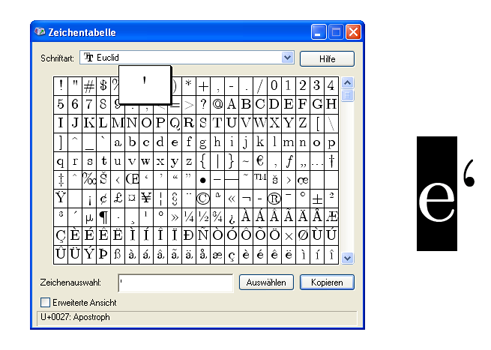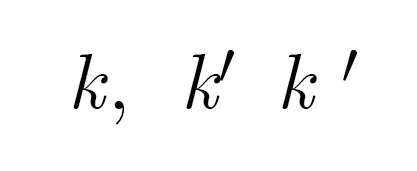
Font: Euclid. Problem: Apostroph = Komma. (ID CS4)
Mein Problem:
Ich will einen Text darstellen mit mathematischem Inhalt. Für Formeln verwende ich die Schriftart Euclid. Wenn ich allerdings ein Apostroph setzen will, sieht es aus wie ein Komma. Setze ich es in Euclid Symbol, ist es zwar oben, aber zu nah am Buchstaben. Setze ich zwischen Buchstabe und Apostroph ein Leerzeichen, ist zu viel Raum(s.Abb.).
Der Text steht schon, in der als letztes genannten Variante. Dies soll aber nun geändert werden. Am liebsten mit der Suchen/Ersetzen-Funktion, echt!
Meine Frage lautet: Wie stelle ich in Euclid das Apostroph korrekt dar? (Die Zeichentabelle zeigt es mir ja richtig an)
du tippst die falschen tasten, auf dem MAC ist es: alt+shift+# ’
ein apostroph sieht auch wie ein komma aus, nur eben oben.
den abstand kannst du ändern wenn du da ein viertel oder achtel geviert einfügst und nicht ein leerzeichen, das geht mit rechten mausklick z. b.
ich denke aber, wenn du den echten ’ hast, wird der abstand von sich aus stimmen.
die falschen tasten also. um ein apostroph zu erzeugen.
jedenfalls gehts jetzt plötzlich mit der ganz normalen tastenkombi shift+#, aber es sieht nicht aus, wie es aussehen sollte.
kopiert hatte ich das ja auch schon.
aber dann ist es wohl gar kein apostroph, das ich suchte, sondern dieses zeichen
welches sich laut beschreibung auf der #-taste befindet, die ich doch ständig drücke, aber ich erhalte jetzt nur ein korrektes apostroph und nicht das aufgeführte zeichen s.o.!
daher nehm ich das von mir gesuchte zeichen jetzt aus euclid symbol.
hab jetzt überall ein achtelgeviert davor gesetzt, sieht ganz gut aus.
Gut, wenn ich das richtig zusammfasse:
du möchtest ein k' (also "k strich") schreiben, der "strich" ist dir aber (durch fehlendes oder unpassendes Kerning der Schrift) zu nah am "k" dran, und mit Leerzeichen zu weit.
Es gibt "nur" folgende Lösung:
Suche dir so eine Textstelle. Markiere das Leerzeichen, und drücke dann STRG+SHIFT+ALT+M. Damit fügst du statt dem Leerzeichen einen "Thinspace" ein, der ist schmaler als das Leerzeichen, aber sollte genug Platz schaffen. Dann kopierst du dir die ganze Passage, und lässt per Suchen-Ersetzen nach "k '" suchen, und ersetzt das ganze durch die kopierte Zeichenkette (der Thinkspace wird als Zeichenkombination im Ersetzenfeld dargestellt, dann aber "richtig" ersetzt - ausprobieren).
nützlicher shortcut, merk ich mir. ich lass das mit dem achtelgeviert jetzt so, ist schon rausgegangen.
achso, und es gibt noch einige mehr variablen als k.
habe daher nach "(leerzeile) ' " gesucht und mit "(achtelgeviert) ' " ersetzen lassen.